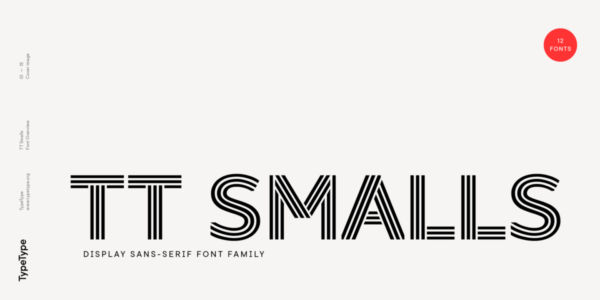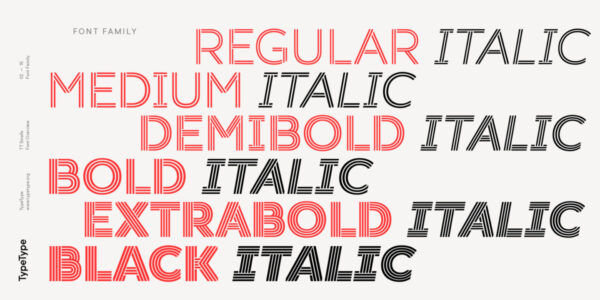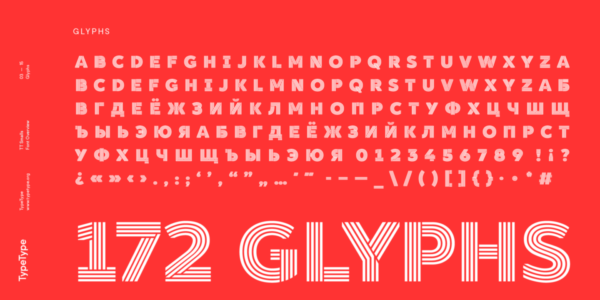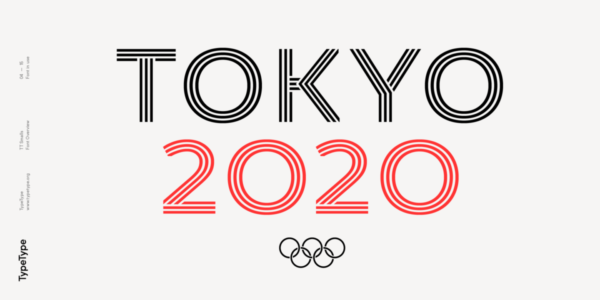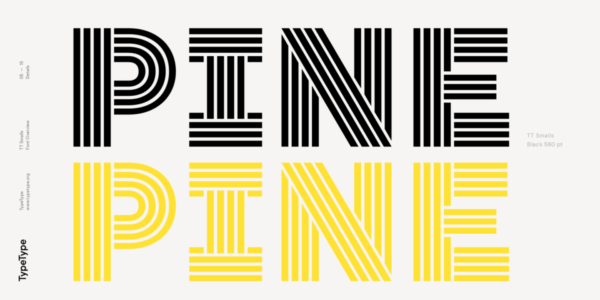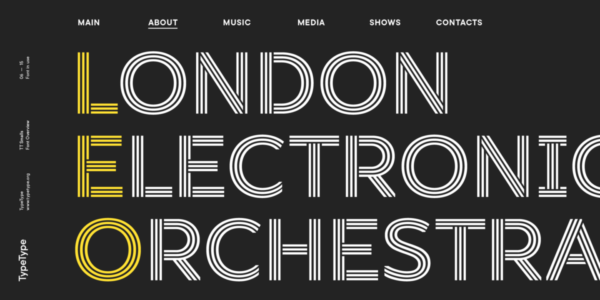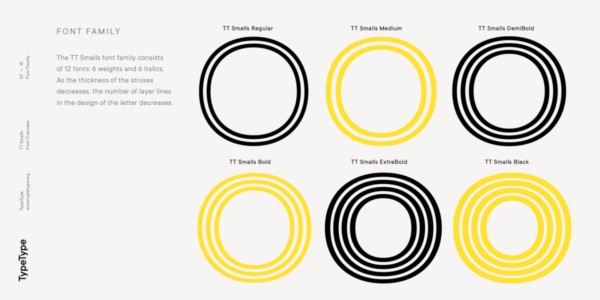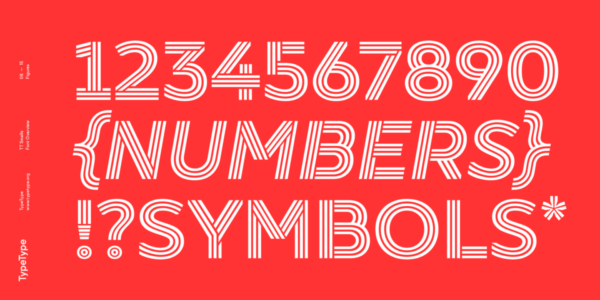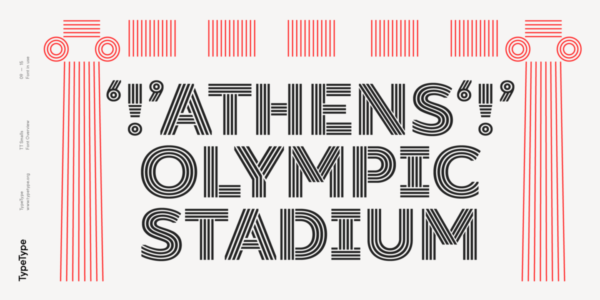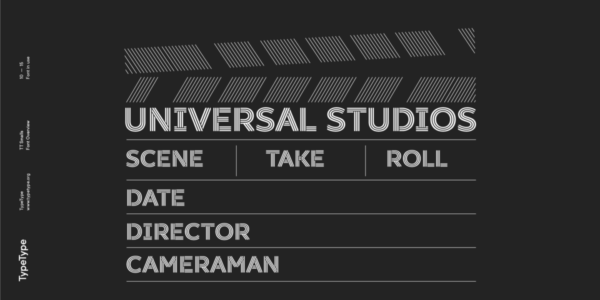
TT Smalls
TT Smalls — ТТ Смоллс
Произносится «ТТ Смоллс». «Smalls» — производное слово от small, в переводе с английского «маленький». Буквы «TT» являются аббревиатурой названия компании.
TT Smalls — декоративный шрифт для ярких акцентов, состоящий исключительно из прописных знаков в inline версии.
Теперь TT Smalls — это декоративная шрифтовая гарнитура, с помощью которой легко привлечь внимание. Оформляйте выразительные заголовки, применяйте в оформлении упаковок или выделяйте текст на сайте. Будьте уверены, что набранный шрифтом TT Smalls текст вызовет интерес аудитории.
Шрифт TT Smalls содержит 12 начертаний: 6 прямых и 6 наклонных. Кассовый состав гарнитуры — 172 глифа.
Стильная и лёгкая в использовании
О гарнитуре TT Smalls
Забудьте всё, что вы знали о TT Smalls, ведь мы перевыпустили шрифт!
Теперь TT Smalls — это декоративная шрифтовая гарнитура, с помощью которой легко привлечь внимание. Оформляйте выразительные заголовки, применяйте в оформлении упаковок или выделяйте текст на сайте. Будьте уверены, что набранный шрифтом TT Smalls текст вызовет интерес аудитории.
Когда-то TT Smalls являлся нейтральным геометрическим гротеском, а inline версия была альтернативным стилистическим сетом. Однако коллекция универсальных шрифтов TypeType обширна, поэтому мы сосредоточились на создании уникального и выразительного шрифта, выпустив обновлённый TT Smalls.
В гарнитуре присутствуют только прописные знаки в inline версии, конструкции глифов основаны на геометрическом гротеске. С увеличением или уменьшением жирности количество штрихов в шрифте меняется в большую или меньшую сторону соответственно.
Стильная и лёгкая в использовании, гарнитура TT Smalls может дополнить коллекцию декоративных шрифтов, привлекающих внимание.
Шрифт TT Smalls содержит 12 начертаний: 6 прямых и 6 наклонных. Кассовый состав гарнитуры — 172 глифа. Присутствует базовая латиница и кириллица, основные знаки пунктуации. В шрифт добавлена стандартная OpenType фича calt.